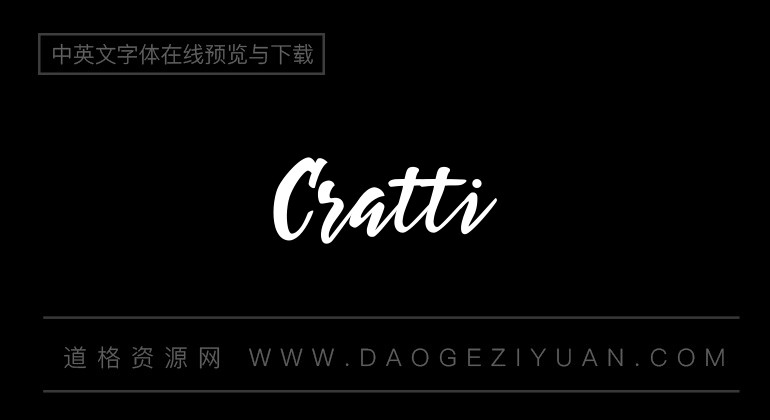
? Cratti 字体是一种简洁而又柔和的英文字体,具有明显的古典风格。它的字体线条细腻,拥有精致的细节,是一种优雅的字体,能够给文字添加温暖感。它的设计灵感来源于古典文学,是一种英文报刊、书籍、网站等多种场景都适用的字体。内容介绍
Cratti是一款非常不错的手写艺术字体,具有很好的视觉感,适合于文化类的宣传设计、商业类品牌的广告和产品包装设计以及个性化文字排版等较多场景。